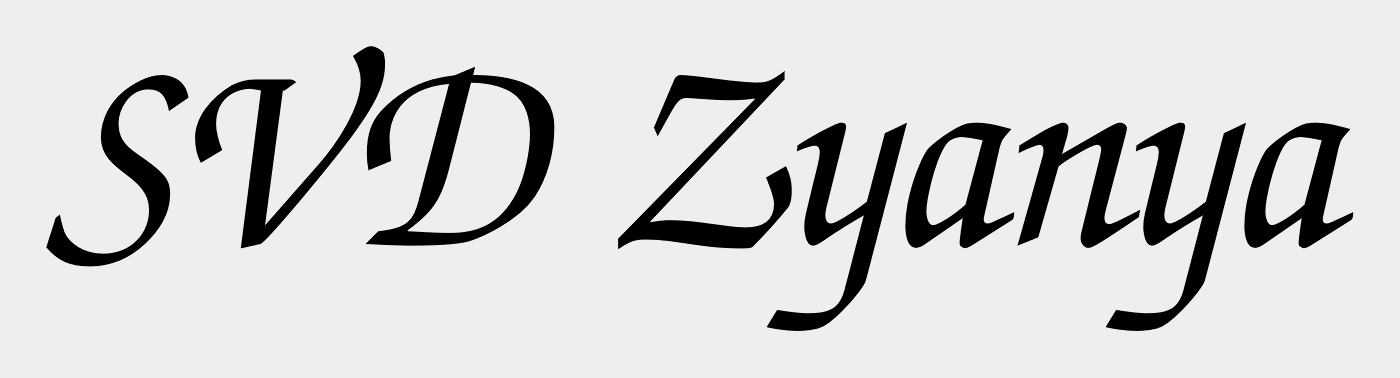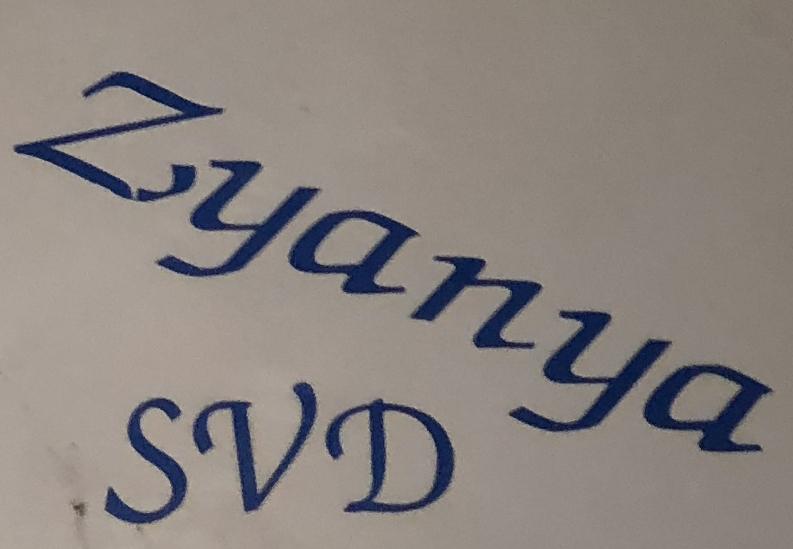
Suche Schriftart für eine Segelyacht
Wir haben eine ältere Font einer großen Segelyacht vorliegen und wie so oft liegt dem Eigner keine Originaldatei oder die Info zur damals verwendeten Schriftart vor.
Bisher wurden wir  leider nicht wirklich fündig und hoffen daher auf Euch.
Bei dem Schriftzug handelt es sich um einen Schiffnamen "Zyanya" und die Clubbezeichnung "SVD". Vermutlich sind beide Worte aus der selben Font abzuleiten.
Die Grafik ist sehr klein und sehr schlecht, eine Erkennung über Generatoren schwierig bis unmöglich.
Habt Ihr da Ideen, welche Schriftart das sein könnte? Markant sind vor allem die Großbuchstaben was die Auswahl einer alternativen Schriftart schwierig macht.
Wenn dein Bild unverzerrt ist, wurde die Schrift künstlich "geradegestellt".